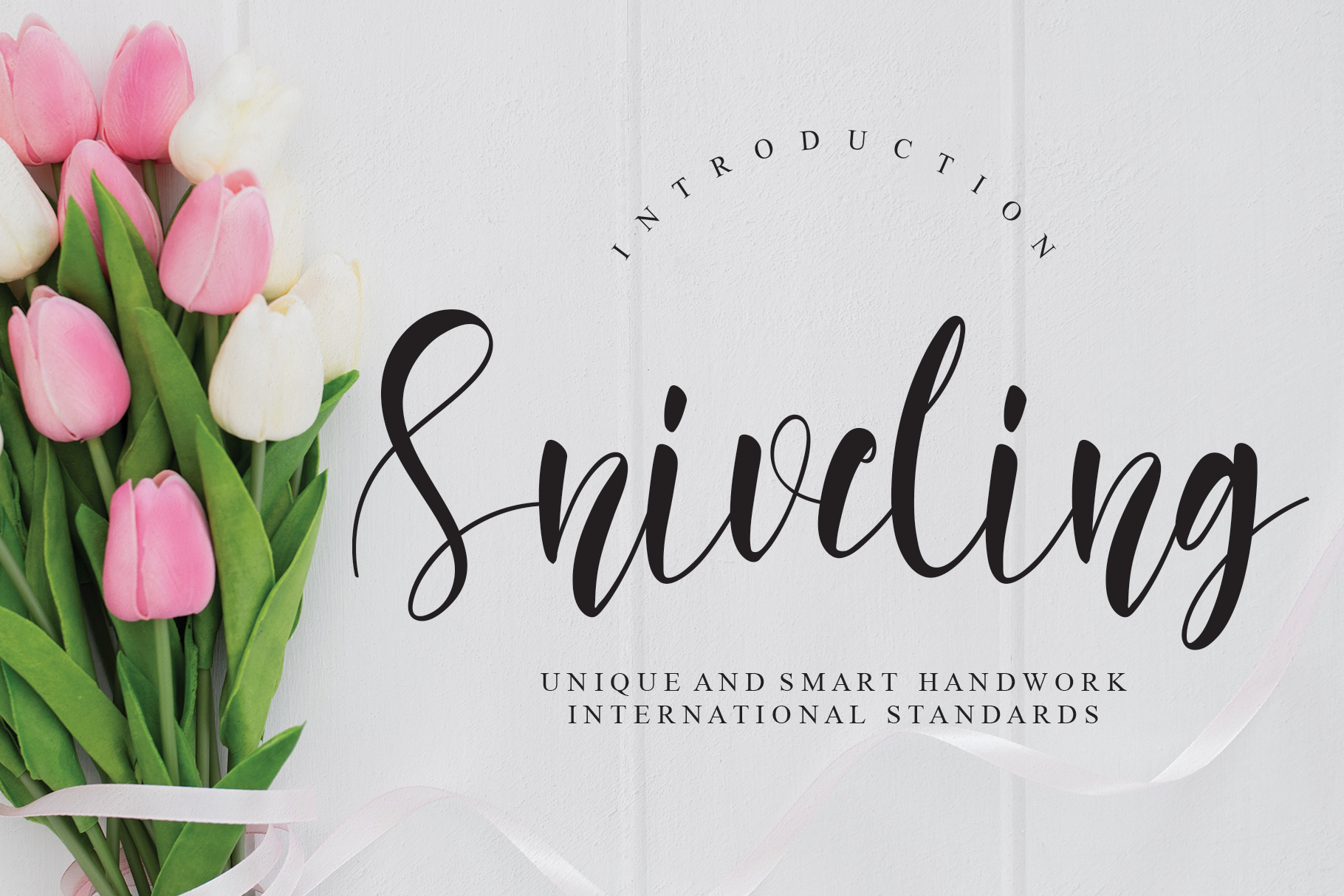
Sniveling Font – Fonte Grátis
Sniveling Font
A Sniveling Font é uma escolha perfeita para quem busca um estilo autêntico e humano nas suas criações digitais. Desenvolvida pelo Designer CreativeLetter, esta fonte de escrita manuscrita oferece a oportunidade de adicionar um toque único à sua proposta, seja ela impressa ou digital. Suas linhas delicadas e nuances naturais criam texturas que se destacam em diferentes formatos e tamanhos. Adapta-se perfeitamente para os mais variados projetos, desde as embalagens de produtos até a personalização de postagens nas redes sociais, logotipos para anúncios publicitários, ou o design dos maiores eventos. Também é ideal para criações gráficas como identidades corporativas, trabalhos fotográficos e mesmo em designs digitais que exigem uma textura quase realística. A Sniveling Font é a escolha certa para quem busca um visual atraente e autêntico em qualquer projeto.